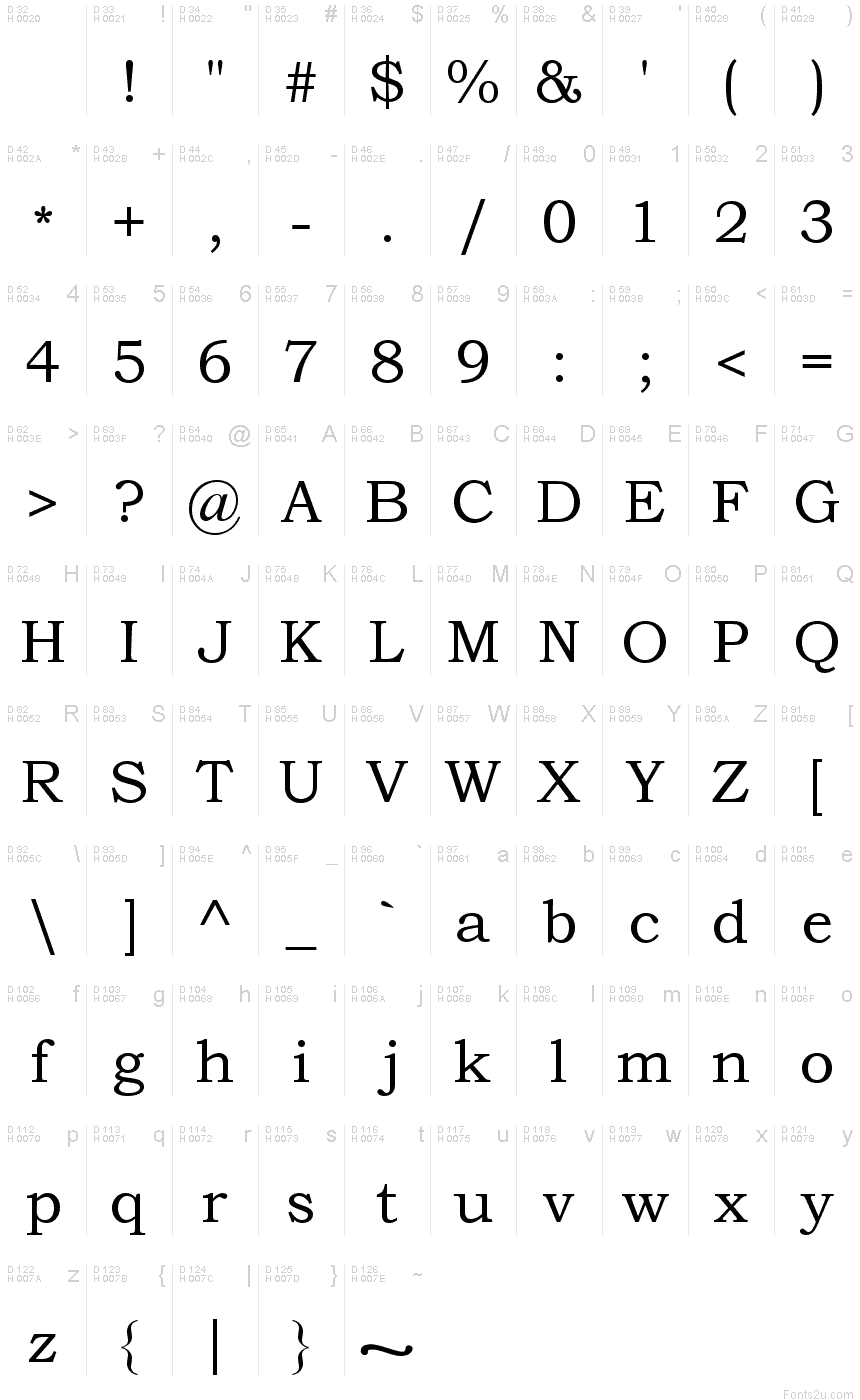
Menaion من تصميم LCAPR و UdSU، هو خط "سيريف" مجاني ذو طابع أدبي هادئ يبعث على الحنين إلى الماضي. تدمج الحروف بين التباين الحاد والزوائد المنحنية برفق والأشكال المفتوحة والمستديرة، مما يمنح الخط طابعاً رسمياً بعيداً عن التكلف.
وهذا يجعله خياراً مثالياً لأغلفة الكتب والملصقات الثقافية وعناوين المجلات وبرامج المعارض وصفحات العناوين، حيث تساعد لمسة من الأجواء التاريخية في إيصال الرسالة. وباعتباره خطاً مجانياً، يعمل Menaion أيضاً بشكل رائع في العناوين التحريرية القصيرة والحروف الاستهلالية الشبيهة بالمونوغرام، إذ تضفي حركته الأنيقة وإيقاع زوائده البارز حضوراً متزناً واحتفالياً حتى على بضع كلمات.